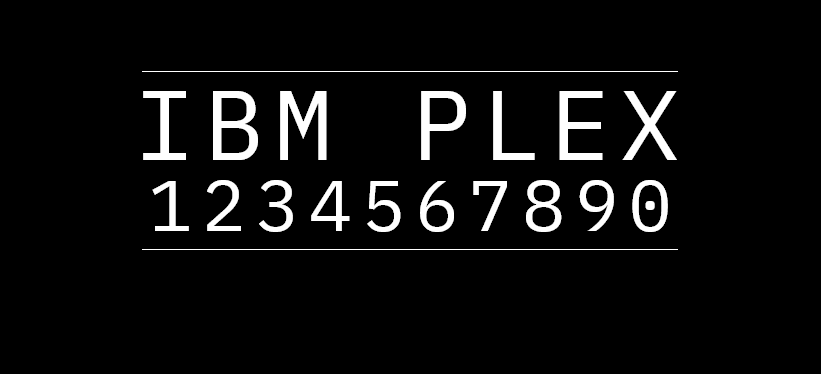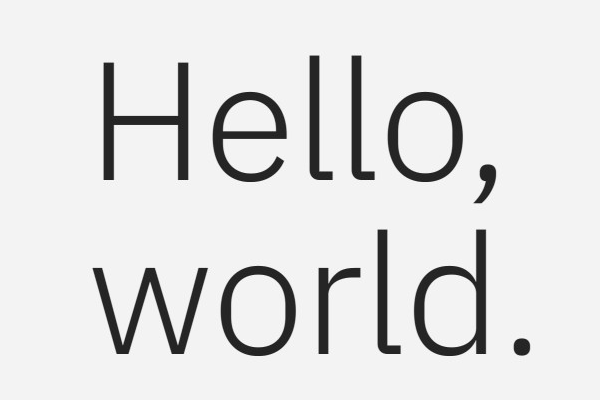
IBM Plex
计算机巨头IBM发布了一款全新的开源字体IBM Plex,旨在替代Helvetica。这款字体有着开放源码的授权,这意味着任何人都可以自由地下载和使用它,而Helvetica则需要支付许可费才能使用。
IBM Plex Family由三种字体类型组成,分别是Sans-serif(无衬线体)、Serif(衬线体)和Mono(等宽字体)。这三种字体类型在英文字型设计中都是非常常见的,每种类别都有八种不同的字重,从Thin到ExtraLight、Light、Text、Regular、Medium、Bold到SemiBold,同时也有为斜体设计的Italic系列。这使得IBM Plex在视觉效果上更加丰富和灵活。
IBM Plex效果预览
IBM Plex字体效果预览